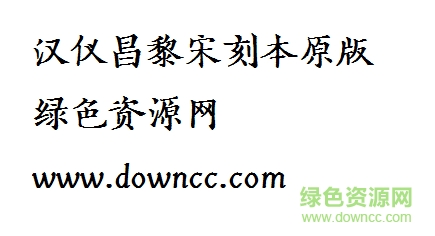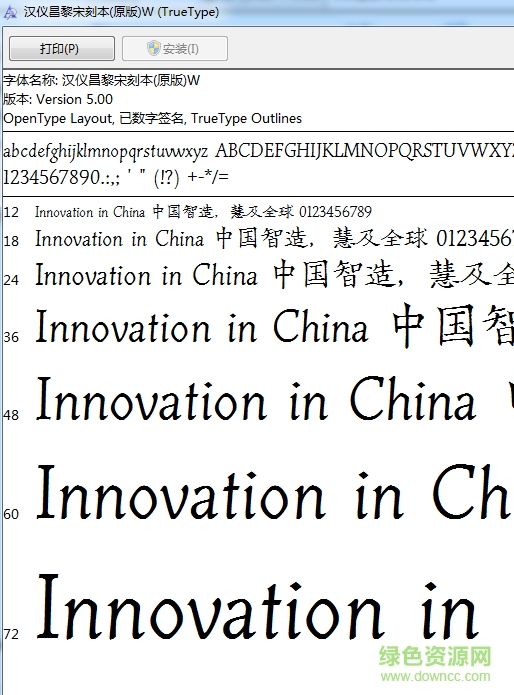
漢儀昌黎宋刻本原版是一款漢儀系列文雅風(fēng)格字體軟件,該字體筆畫有著明顯的點(diǎn)綴藝術(shù),頗有一種毛筆字的脫俗氣息,非常的耐看,喜歡就到綠色資源網(wǎng)下載使用吧!
漢儀昌黎宋刻本原版字體優(yōu)美清新,線條流暢,樸素?zé)o華,飽含古時(shí)之風(fēng)韻,能帶給人們一種懷舊感覺,這種個性的字體適用于傳統(tǒng)產(chǎn)品,民間藝術(shù)品等主題。
風(fēng)格:中國風(fēng)、古典、文藝、復(fù)古、刻本;
推薦場景: 標(biāo)志、廣告、游戲、動漫、影視、包裝、古籍。